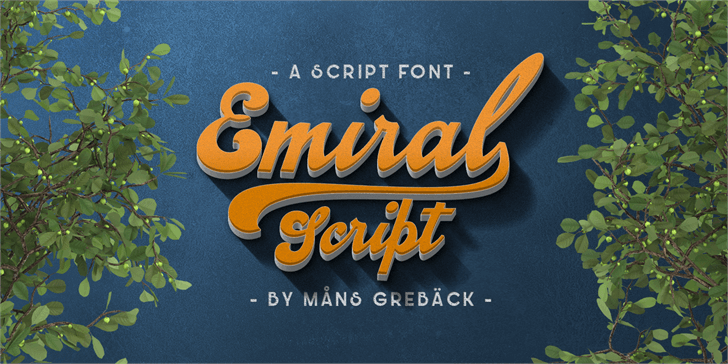
Emiral Script Font – Download Grátis
A Emiral Script é uma tipografia vintage com estilo Regular e Bold, criada por Måns Grebäck. Este script suave e charmoso é perfeito para a criação de logotipos e slogans memoráveis. Suportando centenas de línguas, essa fonte inclui alternâncias contextualizadas e ligaturas, o que permite uma variedade incrível de combinações visuais. É ideal tanto para aqueles desejando um toque vintage em seus projetos como para quem busca uma fonte moderna e versátil. Com a Emiral Script Font, você pode criar mensagens memoráveis em qualquer idioma. Não espere mais: personalize seu design com esta poderosa fonte de script.
Designer: Måns Grebäck